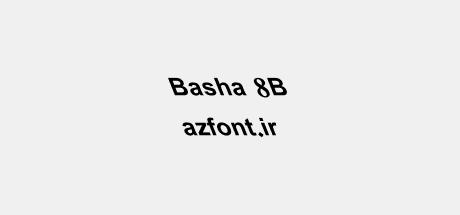
Basha 8B
فونت زیبای رایگان Basha 8B
قلم زیبای Basha 8B Bold Italic از سری قلم های بسیار زیبا برای تایپوگرافی و لوگو تایپ می باشد.این قلم در وزن Bold Italic و توسط Salah Izzeddin AlBasha طراحی و منتشر شده است.
Basha 8B
Bold Italic